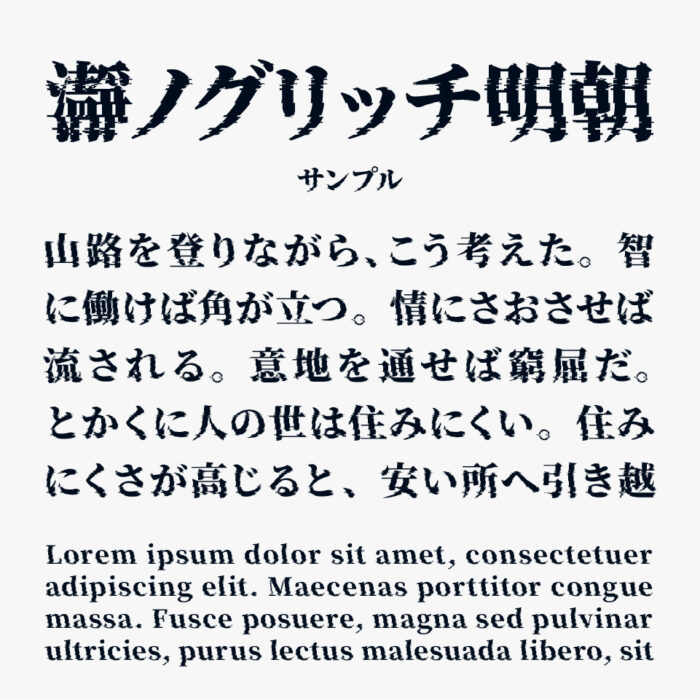
瀞ノグリッチ明朝フォントは、源ノ明朝をベースにグリッチエフェクトの処理を施したかっこいい明朝体のフォントになっています。
ノイズが乱れているようなグリッチ加工が効いたデジタル的なかっこいいフォントに仕上がっています。デジタル的なデザインに明朝体ってマッチしますね。
収録漢字が、Adobe-Japan1-6準拠されているので、ほぼ日常で使う一通りの文字は使えます。
収録文字は、漢字(Adobe-Japan1-6)・ひらがな・カタカナ・アルファベット・数字・記号が収録されています。